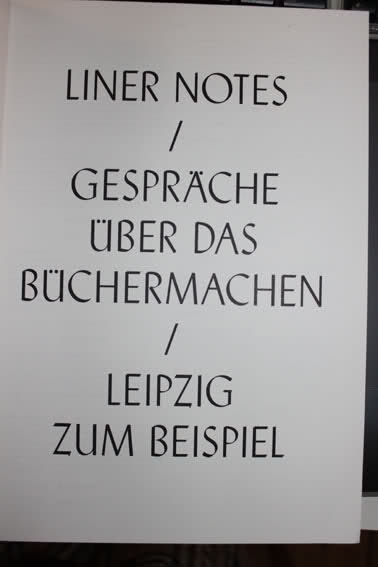
welche schrift ist das?
hier eine Schrift, die in letzter Zeit ständig verwendet wurde, nur welche Schrift ist das?! Könnt ihr mir helfen?
Kann da vielleicht jemand lösen? Ich müsste die doch kennen …
Mir geht es fast genauso. Ich kennen paar Schriften dieser Art, zB die Continental von Aldo Novarese http://www.identifont.com/list?2+Continental+1+AD+70+60M+0+HT7+0, aber alle diese Schriften haben keinen Schaft am großen U. Das macht mich stutzig! Und die mit Schaft haben zuviel Serif (Flare-Serif) ...
wenn es buchdruck ist, könnte es auch die 'Stahl' von Hans Kühne/Rudolf Koch sein.
gibt es meiner kurzen recherche zufolge aber nicht als digitalen font, zumindest nicht unter diesem namen.
nochmal kurz verglichen: ja, es müsste wirklich die 'Stahl' sein. vielleicht findet ja jemand einen digitalen schnitt.
Des Rätsels Lösung kenne ich nicht, … aber nah dran ist auch die CG Lisbon, die zum Beispiel Mirko Borsche für das Thalia Theater einsetzt. Hier in Hamburg sieht man sie eben jetzt auch häufiger im Straßenbild.
Die ist sehr ähnlich zur bereits genannten Lydian und wurde irgendwo (iirc Idenityfont) als eine ähnliche Schrift genannt. Aber wir haben jetzt ja den Urvater dieser Schriften: ,,Stahl''.
Es handelt sich, wie mein Namensvetter findigerweise erklärt hat, offenbar tatsächlich eine digitale Version von Kochs & Kühnes »Stahl« – simply: Steel –, die für Liner Notes angefertigt wurde und (noch) nicht im Verkauf erhältlich ist. – Was man »in letzter Zeit« häufiger sieht, ist wohl aber tatsächlich die genannte Lisbon.
Kleines Suchrätsel: Wer findet die Stahl?